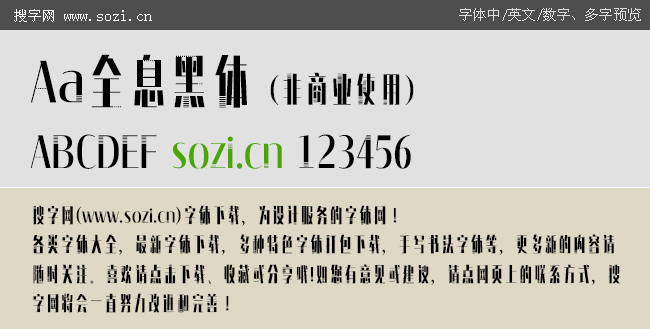
Aa全息黑體
搜字網(wǎng)給大家提供一款A(yù)a全息黑體(非商業(yè)使用)中文字體下載,Aa全息黑體是一款藝術(shù)字體,該字體字體線條粗細適中,筆畫隨性,結(jié)構(gòu)肆意灑脫,具有很好的視覺感。適合應(yīng)用于海報設(shè)計、包裝設(shè)計、網(wǎng)頁設(shè)計等應(yīng)用(此字體為個人非商用版,商用可以聯(lián)系QQ:1006760504)。